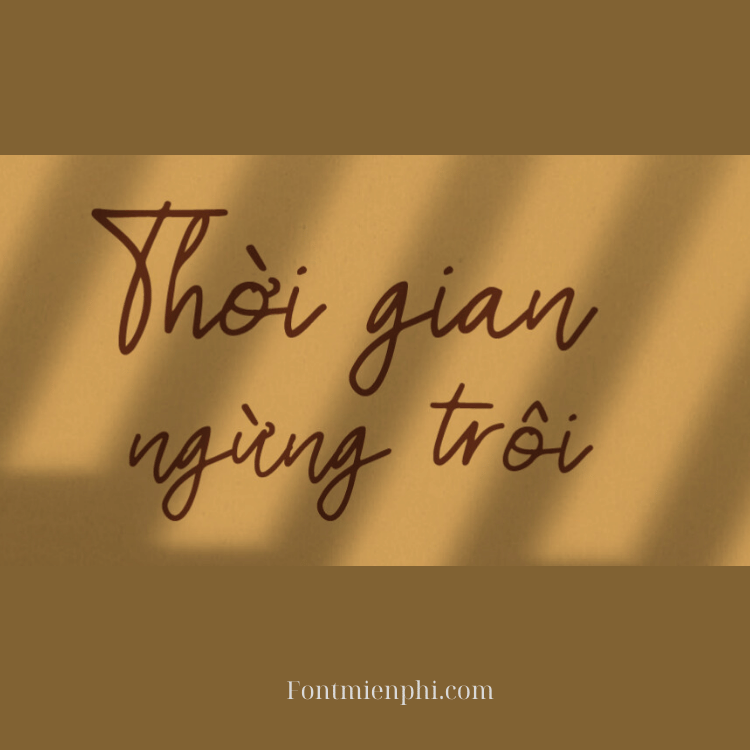
Font Việt hóa VIP Faugllin Balseyn – Phong Cách Độc Đáo, Thiết Kế Chuyên Nghiệp
Font VIP Faugllin Balseyn là một trong những font chữ Việt hóa cao cấp, mang phong cách hiện đại và sang trọng. Với nét chữ tinh tế, độc đáo, font này phù hợp cho các dự án thiết kế đồ họa, logo, banner, hoặc ấn phẩm truyền thông. Được tối ưu hóa cho tiếng Việt, Faugllin Balseyn đảm bảo hiển thị sắc nét, mượt mà trên mọi nền tảng.